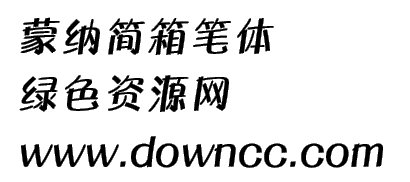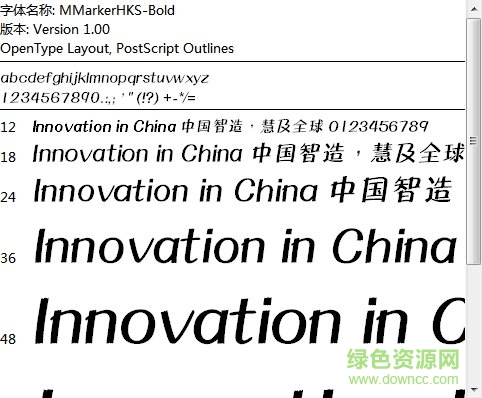
蒙納簡(jiǎn)箱筆體
蒙納簡(jiǎn)箱筆體是蒙娜字體早期推出的一款個(gè)性字體,英文名稱(chēng)為:MMarkerHKS-Bold,筆畫(huà)粗細(xì)結(jié)合棱角分明,整體結(jié)構(gòu)微傾,顯得十分出彩,來(lái)綠色資源網(wǎng)即可免費(fèi)下載!
蒙納簡(jiǎn)箱筆字體特色
蒙納字體為臺(tái)港澳地區(qū)使用的大五碼(BIG5)字體,所以在使用時(shí)不管這字體是簡(jiǎn)體還是繁體的,都必須直接輸入繁體字才能顯示所有文字,如果你輸入的是簡(jiǎn)體字,有的字就顯示為空白了。
蒙納箱筆體簡(jiǎn)體
蒙納簡(jiǎn)箱筆體的部分筆畫(huà)末端微露層次不齊之感,類(lèi)似箱子模板的結(jié)構(gòu),顯得抽象而生動(dòng),字庫(kù)較為完整,部分字體需在繁體狀態(tài)下使用,能滿(mǎn)足設(shè)計(jì)師門(mén)的平面設(shè)計(jì)中的多種需要!